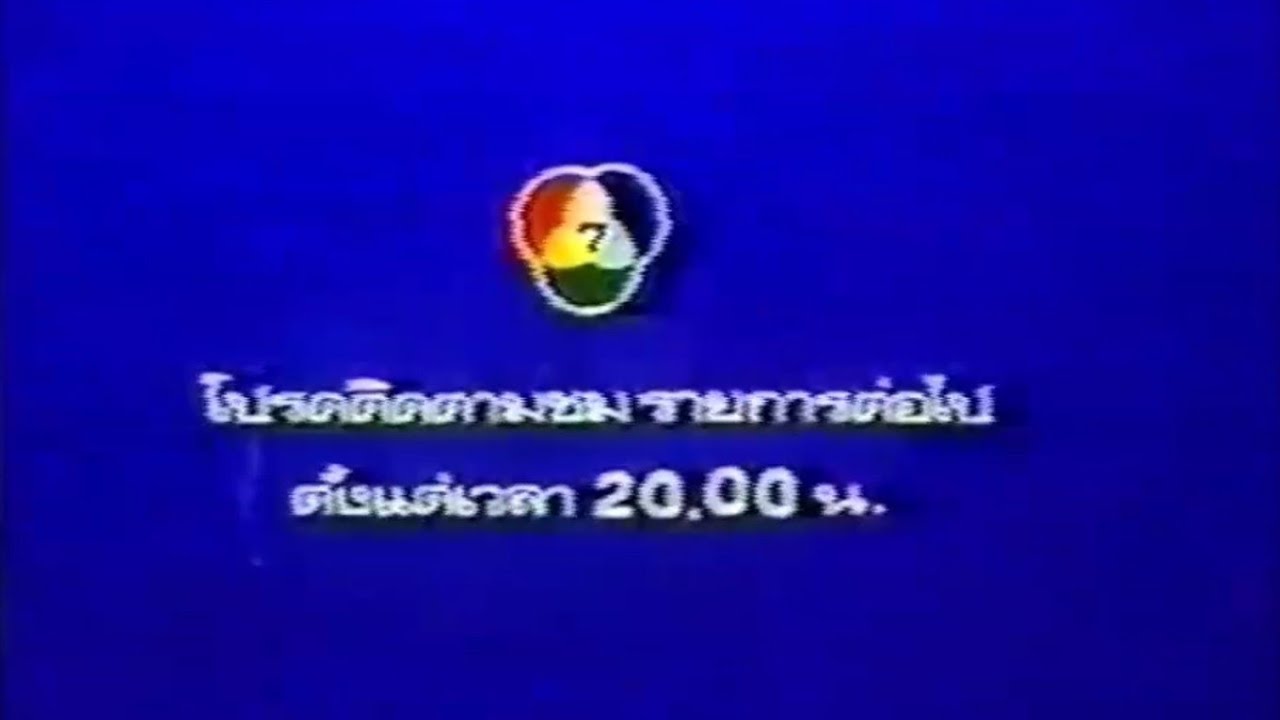
(หาฟอนต์) เป็นฟอนต์ยุคเก่าครับเคยเห?
สวัสดีครับ รบกวนเพื่อนๆ พี่ๆ ใน forum นี้ทีครับ กำลังหา ฟอนต์นี้อยู่เลยครับ
เคยเห็นตามโปสเตอร์ให้ความรู้ต่างๆ สมัยตอนยังเด็กๆอยู่ครับ เช่น โปสเตอร์ให้ความรู้เกี่ยวกับยาเสพย์ติด ฯลฯ ครับ